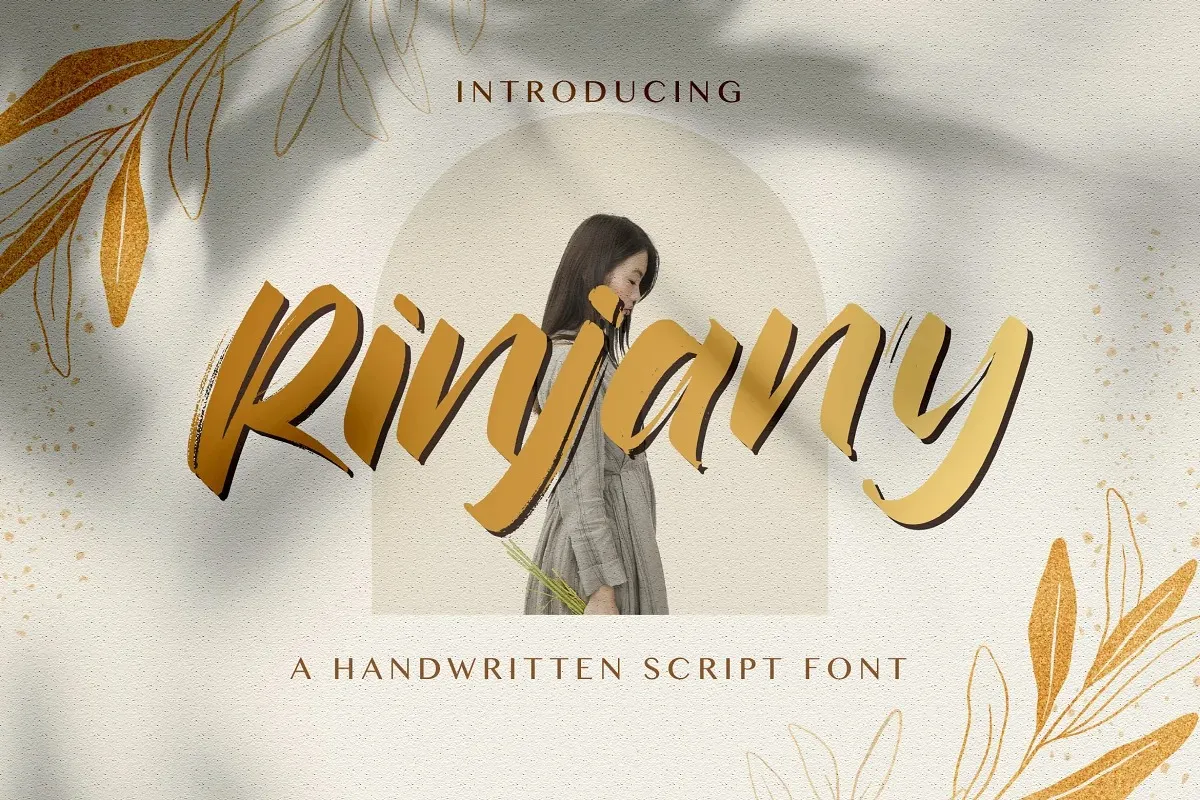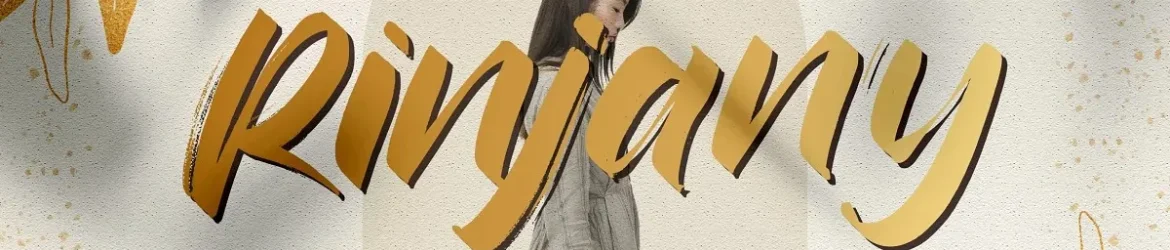
Esta nova fonte criada pela StringLabs é uma mistura única de traços ásperos e texturas com giz seco, projetada para adaptar-se a uma variedade de projetos. Suas linhas fortes e detalhes bruscos oferecem um efeito visual que vai do vintage à contemporâneo. É perfeita para aplicação em branding empresarial, Instagram quotes, cartões de Natal, posters, cabeçalhos de blogs, roupas de moda, comunidades esportivas, filmes, fotografia, hobby ou qualquer outro projeto onde deseje dar um toque especial e único ao seu design. Com sua estética que mistura a arte à técnica manuais, Rinjany Font é uma escolha inteligente para quem busca uma fonte script com personalidade e presença.